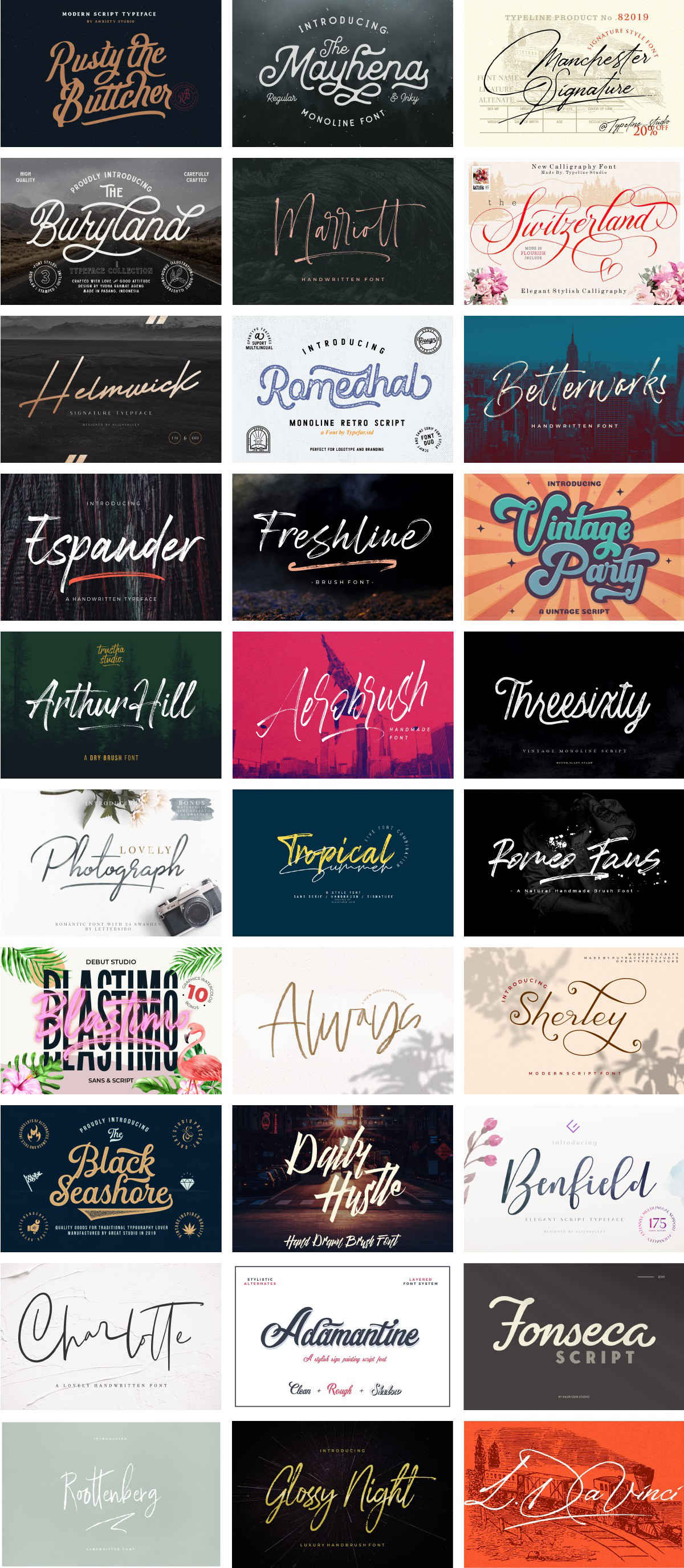
Pixel Surplusでは、フォント集「THE COMPLETE SCRIPT FONT BUNDLE(ザ・コンプリート・スクリプト・フォント・バンドル)」が一ヶ月限定販売中です。
「The Complete Script Font Bundle」の気になる内容
今回のバンドルの中で、私が特に気になるフォントはこちらです。
Manchester Signature
「Manchester Signature」は手書きのサインのようなフォント。写真やイラストに重ねたり、他のフォントとの組み合わせが楽しい書体です。
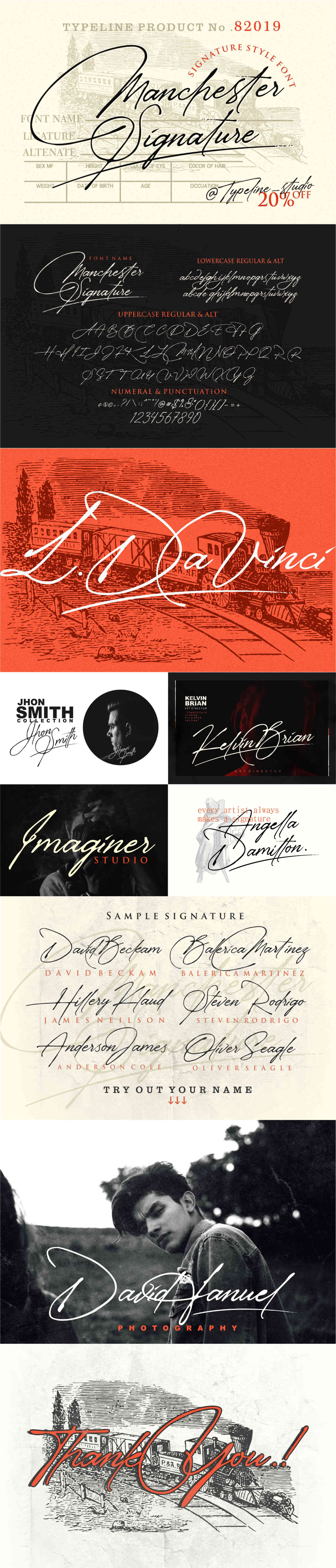
Switzerland
「Switzerland」はハート形のスウォッシュ(飾り)がユニークなフォント。他にもたくさんのスウォッシュが用意されていて、タイポグラフィが楽しくなる書体です。
Always Script
ほどよく力の抜けた、おしゃれな印象を与えたい時にオススメの「Always Script」。写真やイラストに重ねる時に使いたいSVGフォント版もあります。
Roottenberg
「Roottenberg」は女性の手書き文字のような優しい印象の、Pixel Surplusのオリジナルフォント。このフォントはこちらから1点だけでの購入も可能です。
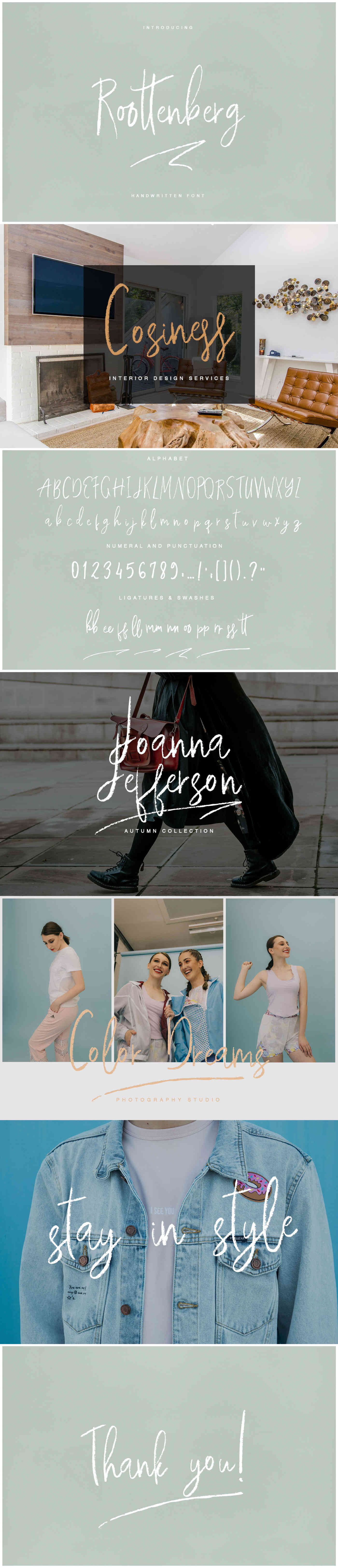
Daily Hustle
「Daily Hustle」はマーカーで書いたようなラフな雰囲気のPixel Surplusのオリジナルフォント。このフォントはこちらから1点だけでの購入も可能です。